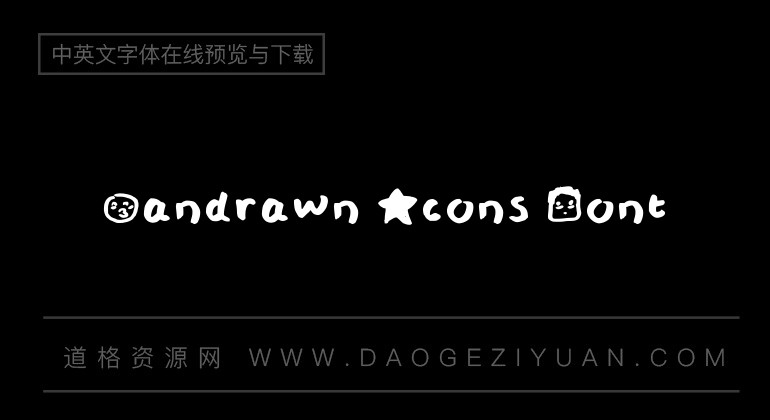
Handrawn Icons Font
Handrawn Icons Font 是一种手绘图标字体,其中包含了各种手绘风格的图标,如箭头、星星、心形、勾选框等等。这种字体可以在设计中使用,为文档、网站或其他项目添加一些个性化的元素。 相较于传统的图像文件,使用字体图标有一些优点。首先,它们可以缩放而不失真,所以无论应用在何种大小的设计项目中都能够保持清晰度。其次,它们可以轻松地更改颜色和大小,以适应不同的设计需求。最后,使用字体图标可以减少页面加载时间,因为字体文件比图像文件更小,更快速地加载。 Handrawn Icons Font 是一种非常有趣和独特的字体,可以为设计师提供很多创造性的可能性。
Handrawn Icons Font是一款非常不错的手写艺术字体,具有很好的视觉感,适合于文化类的宣传设计、商业类品牌的广告和产品包装设计以及个性化文字排版等较多场景。